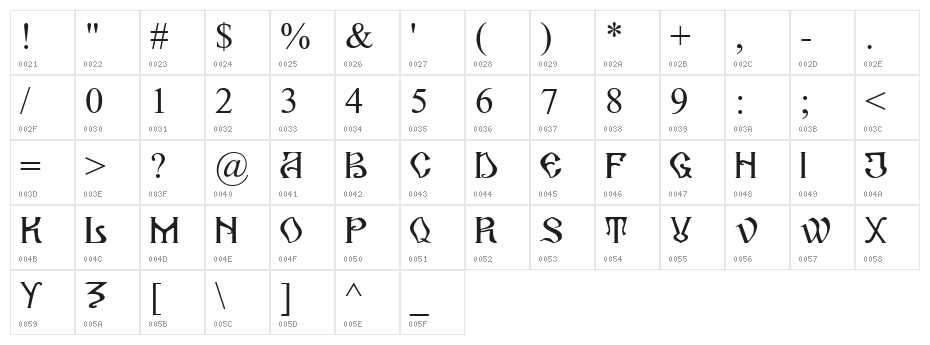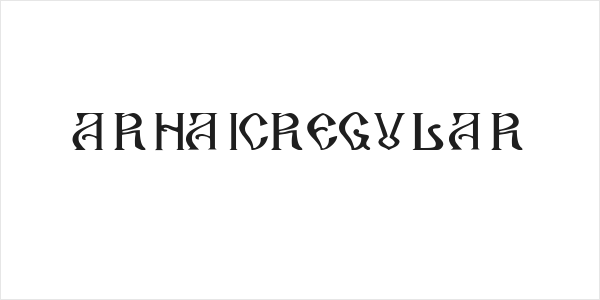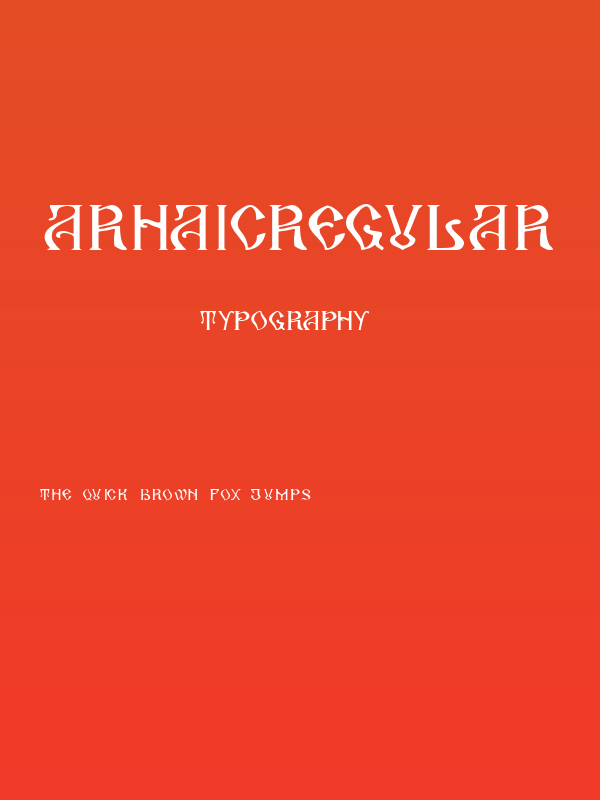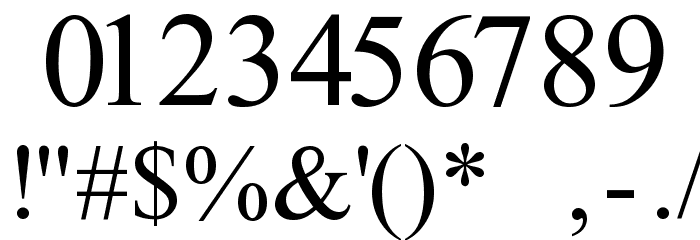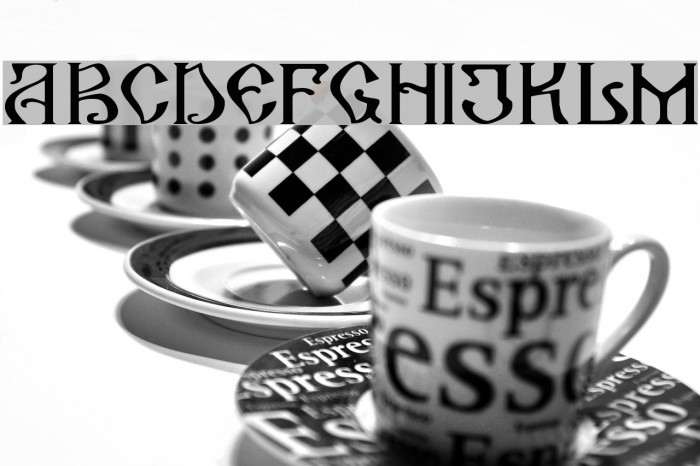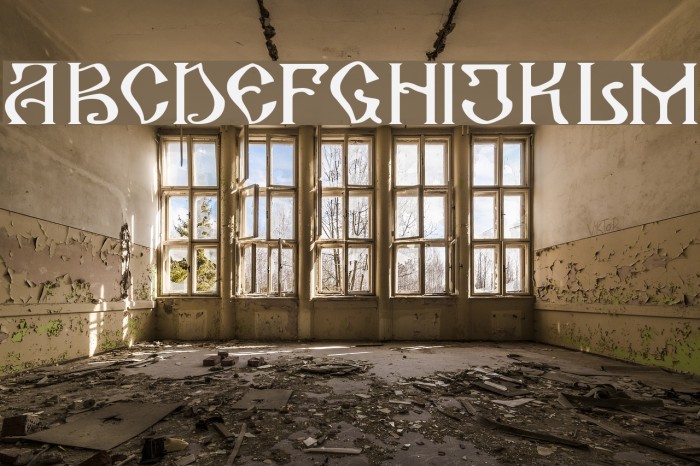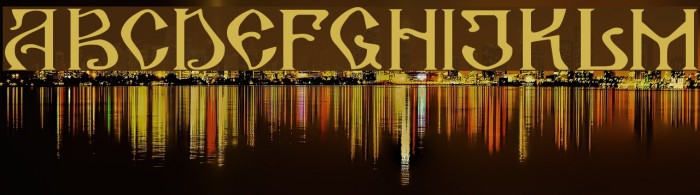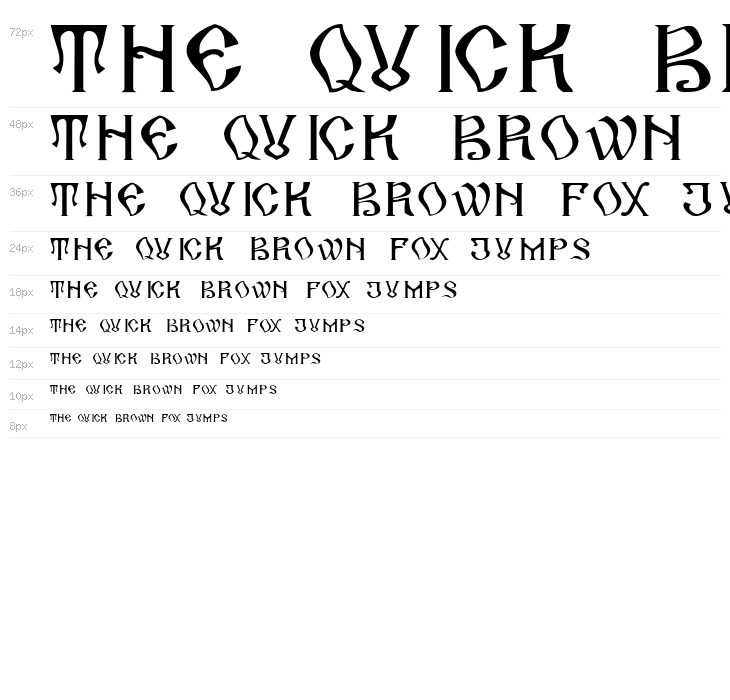
ArhaicRegular Font
| Gesamtstil | Vintage |
| Anwendungsfall | Logos, Headlines, Branding |
| Vorgeschlagene Projekte | Ideal for projects that require a strong, authoritative presence such as logos, branding, book covers, or historical-themed designs. |